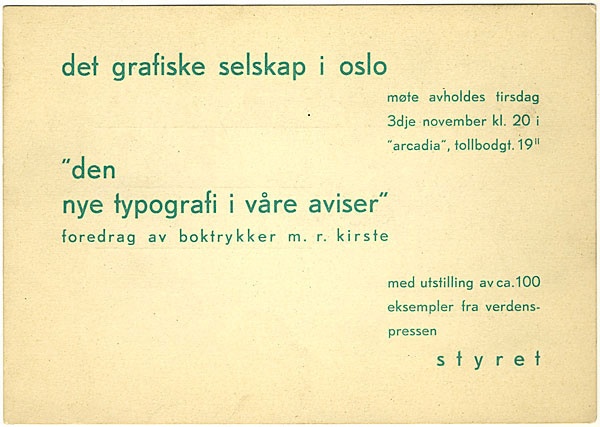
Første verdenskrig (1914–1918) var et tidsskille i politikk, samfunnsliv og kultur. Mange ville kaste over bord verdiene og institusjonene til det gamle samfunnet, som hadde ført verden ut i en grusom krig. Samtidig fikk den tekniske utviklingen større fart enn noen gang tidligere. Innen arkitekturen og andre formgivingsfag vokste den radikale stilretningen funksjonalismen fram.
Innenfor typografien fikk denne retningen navnet «den nye typografien» eller «elementær typografi». Den angrep de tilvante oppfatningene innen boktrykkerfaget, og fikk raskt en sterk stilling, også i Norge. Den hevdet fornuft, klarhet og enkelhet i formgivingen. Funksjonen til en trykksak skulle bestemme dens form – pynt og personlig preg skulle skrelles bort.
Invitasjonskort til et møte i Det grafiske selskap, trolig i 1930. Formen har flere av den nye typografiens kjennetegn: asymmetri, groteske skrifttyper (dvs. skrift uten seriffer og med tilnærmet lik strektykkelse) og kun minuskler.
Det er i dag stor interesse for funksjonalismen, i Norge så vel som i andre land. I Norge har dens innvirkning på særlig arkitekturen blitt grundig behandlet. Men dens innvirkning på de grafiske fagene i Norge hadde ikke blitt belyst før jeg publiserte en artikkelserie i det tidligere medlemsbladet for Norsk grafisk forbund, Norsk grafia. Artiklene er et resultat av en gjennomgåelse av alle relevante fagtidsskrifter, vurderinger av arbeider i den nye stilen, og intervjuer med eldre fagfolk.
Historisk godbit! Jan Tschicholds manifest «Grunnreglene for elementær typografi» er et sentralt dokument. Her i Harald Clausens oversettelse fra 1930.
Trond Klevgaards The New Typography in Scandinavia: Modernist Design and Print Culture fra 2020 er en grundig analyse av samme periode, sett i et skandinavisk perspektiv. Jeg har anmeldt boka her.
ENGLISH SUMMARY
This series of three articles, first published in 1998, describes the national and international background for the modernist, functional so-called «new typography» of the interwar years. It studies its main spokespersons in the Norwegian printing trade, the trade press and the first publications which applied the new principles. The «new» (or «elementary») typography rapidly established a strong presence in Norway, and reached its zenith in 1930.
PIONERER FOR DEN NYE TYPOGRAFIEN
Disse tre personene kan eksemplifisere hver sin del av artikkelserien: øverst den tyske formgiveren Jan Tschichold, teoretiker for den nye typografien, især på 1920-tallet – i midten Arthur Nelson, den som først hevdet disse nye ideene i Norge, gjennom sitt fagtidsskrift Norsk trykk, mest entusiastisk i 1930 – til høyre den anerkjente Oslo-boktrykkeren Max Rich. Kirste, som tok opp de nye prinsippene i sitt mangesidige virke og i sine lærebøker omkring midten av 1930-tallet.